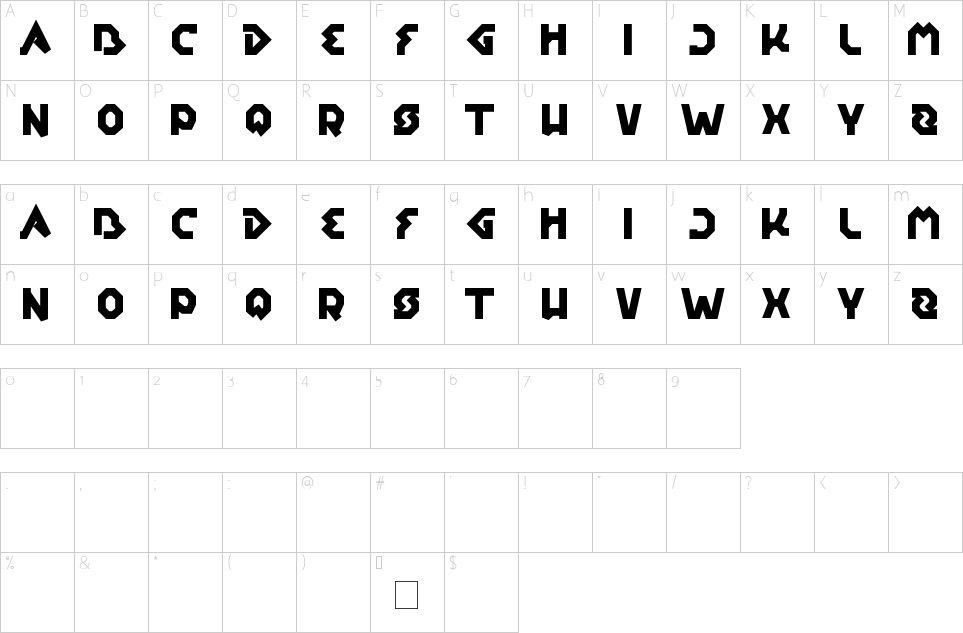
Aqui está uma descrição envolvente e natural para a página de download da font ‘Earth Aircraft Universe Font’, focada em seu uso para o desenvolvimento de recursos gráficos: A ‘Earth Aircraft Universe Font’ é mais do que apenas uma fonte. Essa fonte é uma obra de arte no design gráfico, criada com uma visão visionária que vai além da simples utilização. Suas linhas fluidas e formas geométricas evocam uma visão do universo, com inspirações terrestres e aeronáuticas que complementam-se em harmonia. Com um design cuidadosamente concebido pelo designer indeterminado ‘weknow’, esta fonte proporciona a você uma versão gratuita para uso em Windows e Mac. Embora o design não tenha sido elaborado com ênfase em características específicas, sua utilidade é inegável no trabalho de design gráfico, especialmente em projetos que visam transmitir um sentimento de expansão do universo. Esta font traz um toque de sofisticação e criatividade a qualquer projeto, seja para aplicações de design digital ou impressão digital. Quem sabe, talvez ela inspire você a fazer algo que vai além das superfícies e mergulhe ainda mais no universo que nos rodeia. Seja você um designer gráfico, um criador digital ou um entusiasta do design, a ‘Earth Aircraft Universe Font’ está aqui para fornecer uma base sólida e atraente para seus trabalhos.